アニメ・マンガ・ゲームをヒントに制作されているフリーフォント
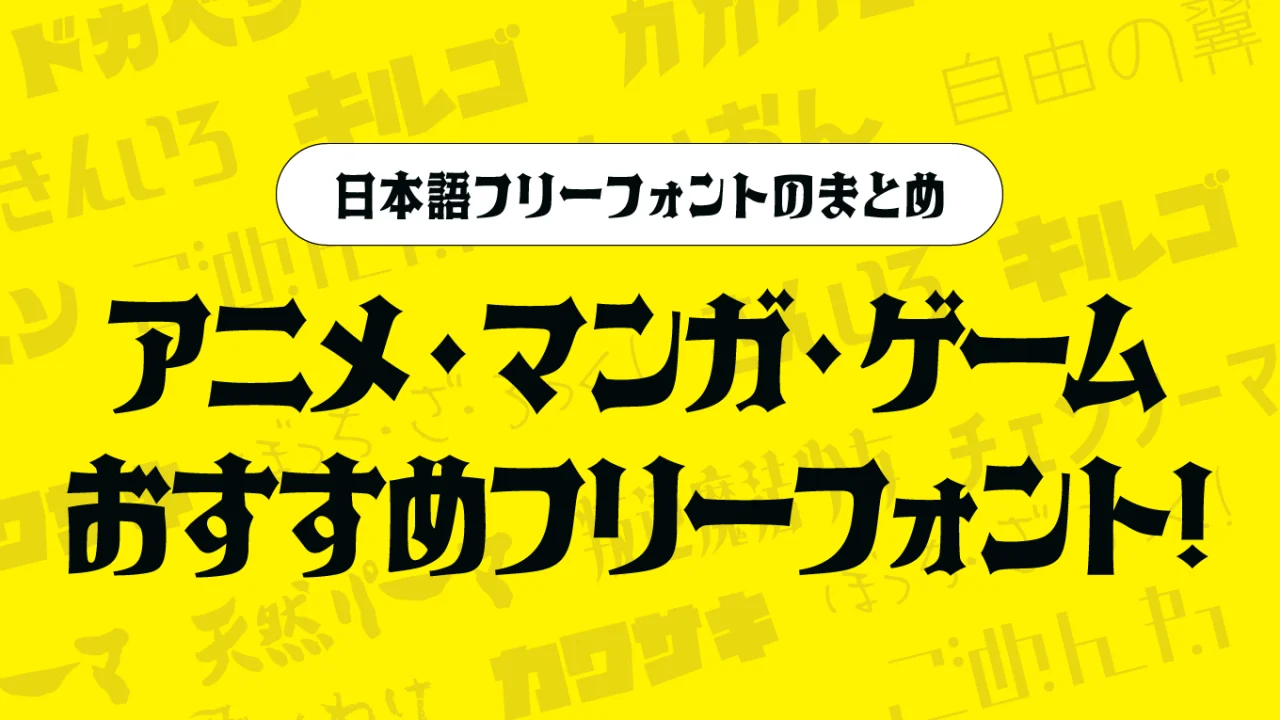
今回は、「アニメロゴをヒントに制作したフォント」「マンガタイトルをモチーフにしたフォント」「あのゲーム内で使用されているフォントに似ている」などのアニメ・マンガ・ゲームに向いているポップな雰囲気がステキなフリーフォントをご紹介します。
「ああこのフォント、見たことある〜」と思うようなフォントから、似ているだけで全然違うフォントだったりするものもあるので、まったく同じというわけではないフォントもありますのでご了承ください。
また同人誌、マンガ、Vtuberのサムネイルやロゴなどを作る際にぜひ取り入れてみると楽しげな雰囲気になるポップなフォントばかりなので、ぜひ参考にしてみてください。
アニメ・マンガ・ゲームをヒントに制作されているフリーフォントのまとめ
以下のサンプルは、本記事で紹介しているフォントの一部ですが、アニメ・マンガ・ゲームなどをヒントにデザインされたタイトルロゴのように使えるポップな雰囲気がとってもステキなフォントばかりです。
きんいろサンセリフ【アニメ:きんいろモザイク】
人気4コマ漫画『きんいろモザイク』のタイトルロゴをモチーフに制作されたフォントです。
アニメタイトルのロゴからモチーフとしているので、ユニークなフォルムがポップな印象がでるので、同人誌のタイトルロゴデザインに取り入れても面白いかもしれません。
Youtubeのサムネイルやテロップでよく使用されているフォントの1つです。
こはるいろサンレイ【アニメ:きんいろモザイク】
「きんいろモザイク」アニメ内ででてくるロゴの「ハロー!!」を文字をモチーフに制作されたフォントだそうです。
フォントもユニークなフォルムがポップで可愛らしい印象なので、アニメ系デザイン以外でも子供向けなどのカワイらしいデザインとの相性とても良さそうです。
カガクゴ【アニメ:カガクチョップ】
人気マンガ「カガクチョップ」のタイトルロゴをモチーフに制作されたフォントです。
アニメからモチーフとしているので、文字のところどころに入っている雷マークのユニークでインパクトがでる文字です。バナーや動画アイキャッチなどのタイトルやキャッチコピーに取り入れることでインパクトがでるんじゃないでしょうか!
キルゴU【アニメ:キルミーベイベー】
人気マンガ「キルミーベイベー」のタイトルロゴをモチーフに制作されたフォントです。
ゴツゴツしたフォルムがポップでドンっとしている強め印象になるので、バナーや動画アイキャッチなどのタイトルやキャッチコピーに使うとインパクトがでること間違いなし!
こちらもYoutubeのサムネイル画像やテロップなどでよく利用されているフォントの1つです。
GLT-ごぬんね【アニメ:少女終末旅行】
TVアニメ「少女終末旅行」に登場する文字をモチーフにしたフォントです。
全体的なフォルムは、直線的なラインや、点が丸形になっていたり少し、SFっぽい未来感のある超ユニークな文字になっているのが特徴的です。
まるこいあす【アニメ:恋する小惑星】
漫画・アニメ「恋する小惑星」のロゴを参考して作成されたフォントです。
文字の中で星が流れているようなデザインがとてもステキです。
バナナスリップ【マンガ:チェーンソーマン】
マンガ「チェーンソーマン」のタイトルロゴの雰囲気に似ているフォントです。似ているだけで全然別フォントなので、ご注意ください。
太くて強い骨格と、微かな可愛らしさが絶妙なフォントです。堅苦しくはしたくないし、可愛すぎるのもちょっと違う、みたいなシーンのときにはピッタリなフォント!
アームド・レモン【マンガ:ぼっち・ざ・ろっく!】
アニメ「ぼっち・ざ・ろっく!」の題字タイトルで使用されているフォントです。
けいふぉんと!【アニメ:けいおん】
アニメ『けいおん!』のロゴタイプをヒントに作成したフォントです。
かな文字が動きがあり軽快でポップな印象になっているので、ベタ打ちだけでも十分楽しげな雰囲気に変えることができるフォントです。アニメロゴで使われたタイプに似せているため、とってもカワイイフォルムで、同人アニメや動画のアイキャッチなどに使うとインパクトやデザイン性が出そうで素敵ですね。
ラノベポップ【アニメ:けいおん】
アニメ「けいおん」のタイトルロゴっぽさも感じるラノベPOPフォントです。
イラストと組み合わせ使うことでラノベのようなタイトルロゴや表紙デザインに仕上げることができます。そのまま打ち込むだけでも十分かわいいフォントですが、斜体にしてみたり、もじをズラして配置してみるだけでラノベのような楽しげな雰囲気があるタイトルを作り出すことが可能です!
カワサキ マッド ドッグ【アニメ:ガールズバンドクライ】
カワサキ マッド ドッグフォントは、アニメ「ガールズバンドクライ」のタイトルロゴをインスパイヤして作られた極太系のデザインフォントです。
うずらフォント【アニメ:ゆるゆり】
人気アニメ「ゆるゆり」のOPで使用されたフリーフォントです。
登場人物とかわいいらしい印象と、手書き風のフォントがゆるゆりに登場するキャラのイメージとぴったり合いますね。
殴り書きクレヨン【マンガ:俺の妹がこんなに可愛いわけがない】
ラノベが原作の人気アニメ「俺の妹がこんなに可愛いわけがない」のタイトルで使われていたクレヨン風手書きフォントです。
クレヨンで描かれた手書きフォントは珍しいので、アニメ関係なく子供向けのデザインや動画など可愛らしい表現をする際などにもピッタリのフォントかと思います。
大甘書道(太甘書道)【アニメ:銀魂】
大甘書道体フォントは、アニメ「銀魂」の次回予告画面で使用されていた文字をベースに作られてた筆文字系のフォントです。極太の筆文字でインパクトあるフォントです。
自由の翼【アニメ:進撃の巨人】
自由の翼フォントは、『進撃の巨人』第二期オープニングテーマで使用されている書体をマネて作られてフォントです。
叛逆明朝【アニメ:魔法少女まどか☆マギカ】
叛逆明朝(Hangyaku)フォントは、魔法少女まどか☆マギカ劇場版のロゴをモチーフとしたフォントです。エレガント&ゴスロリな雰囲気をもつかっこいいデザインのフォントです。
ドカベンフォント【マンガ:ドカベン】
ドカベンフォントは、アニメ「ドカベン」のロゴをヒントに制作して作られたカタカナフォントです。どっしり太めのかっこいい仕上がりになっています。
邪神ちゃんゴシック【マンガ:邪神ちゃんドロップキック】
邪神ちゃんゴシックフォントは、漫画・アニメ『邪神ちゃんドロップキック』のロゴをヒントに制作されたカタカナフォントです。
ポプらむ☆キュート【少女漫画】
少女マンガ雑誌「りぼん」などの少女向けマンガなどに使われていそうな丸みがある可愛くポップなレトロな趣を感じる文字になっています。
古すぎず、昭和過ぎず、ちょうどいい具合のコミカルな仕上がりに作られたフォントになっています。
はちまるポップ(Hachi Maru Pop)【少女漫画】
上記「ポプらむキュートフォント」と似ている部分もありますが「はちまるポップ」は80年代頃に流行した丸文字にインスパイアされて、現代風にアレンジされたデザインの丸文字系フォントです。
こちらも同様に80〜90年代の少女向けマンガなどに使われていそうな丸みがポップな印象がありとっても可愛らしい文字になっています。現代風にアレンジされていますが、レトロな印象もあります。
フィバ字【ゲーム:ぷよぷよ!】
人気ゲーム「ぷよぷよ!」の漫才デモでキャラクター名に使われていた文字をモチーフに制作されたフォントです。漢字が含まれていないので、漢字は他のフォントに置き換えが必要になります。
ぷよぷよっぽいポップで弾けている文字がとっても可愛らしいですね。
マルモニカ【ゲーム:ドラクエなど】
「ドラクエ」などの昔のファミコンやゲームボーイのような昔のゲーム画面のようなレトロな雰囲気で、少し丸みを持ったピクセル文字になっています。
ゲーム系のデザインや動画などと相性がとっても良いです。
いかほ【ゲーム:スプラトゥーン】
スプラトゥーンのゲーム内で使用されているフォントにも似ていることもあり、とても人気のフォントです。
ラインが極太だが、文字先が先細っていくフォルムは可愛くもあり、インパクトもあるフォントです。
ウマ娘ゴシック【ゲーム:ウマ娘 プリティーダービー】
ソーシャルゲーム「ウマ娘 プリティーダービー」のロゴ下部分やガチャ画面で使用されている書体をベースに制作したカナフォントです。
商用利用可ということで、「ウマ娘 プリティーダービー」をパロディとした動画やデザインなどに使用すると、ゲームの世界観に近づけるかもしれません。カタカナのみ収録されているフォントなので、ひらがなや漢字は別フォントと混植がおすすめです。